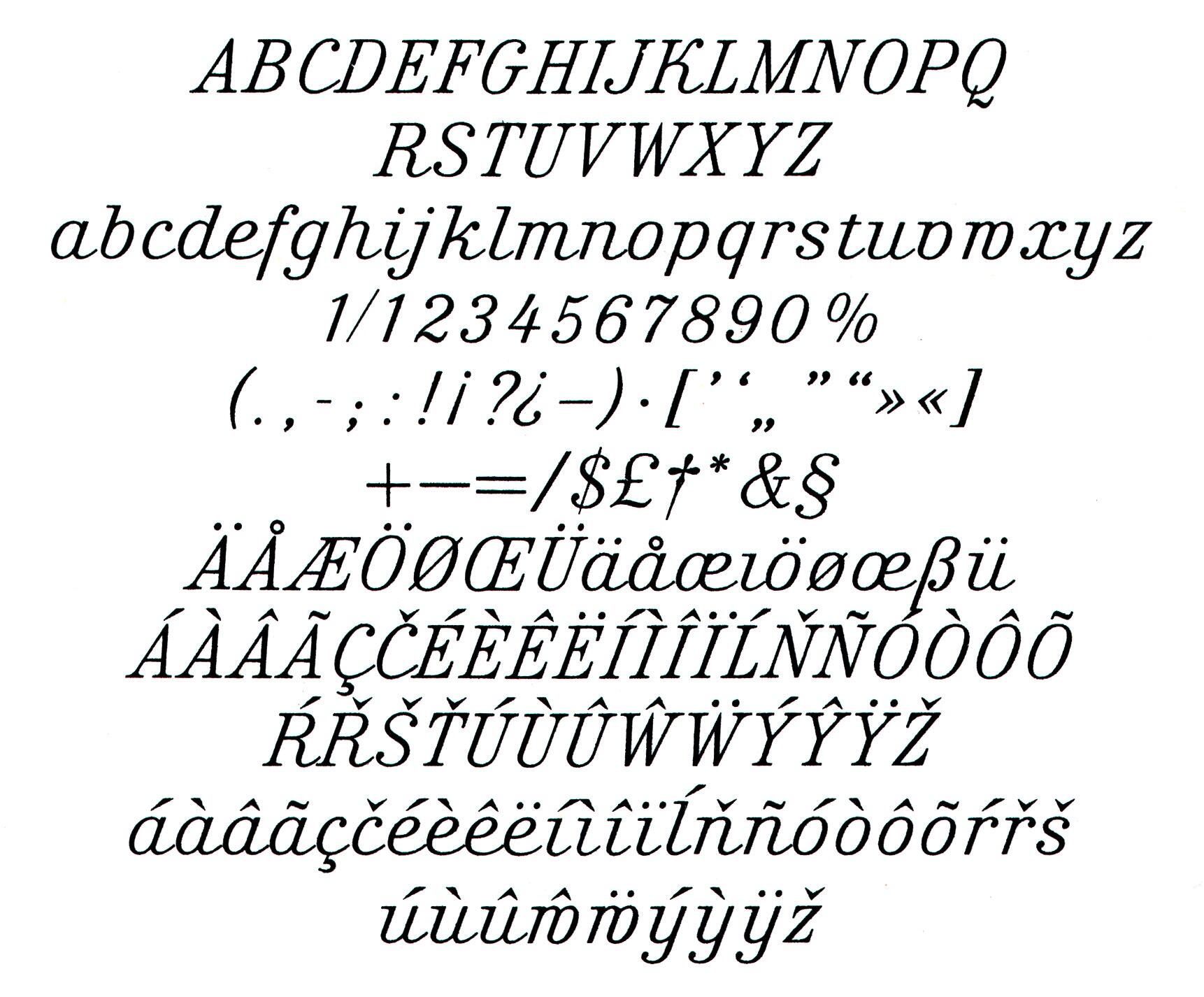
Font-Wiki: Kursivschrift
Die Kursivschrift war neben der Römisch und der Venus eine typische Schriftart für die Beschriftung von Kartenmaterial. Zur möglichst klaren Unterscheidung verschiedener Kategorien auch bei einfarbigen Drucken verfügt die Schrift neben unterschiedlichen Strichstärken auch über verschiedene Neigungen.